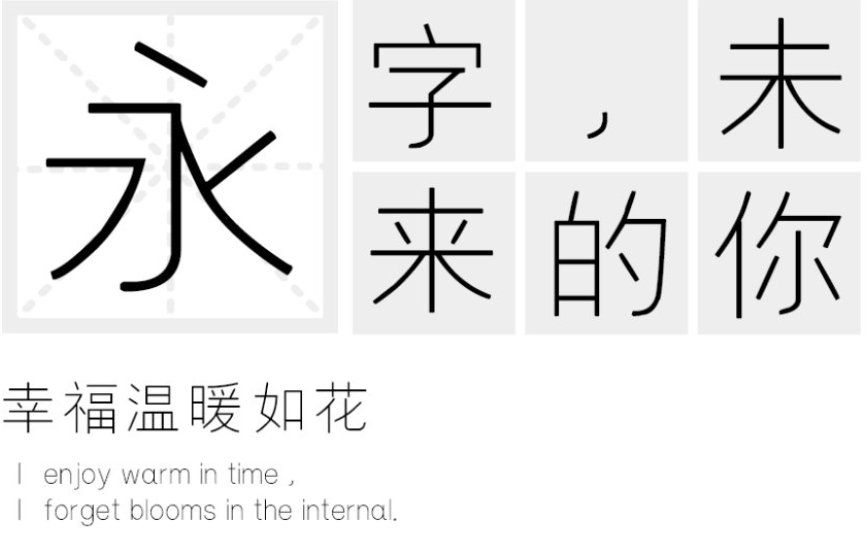
汉标细黑体发布
字体名称:汉标细黑体
字体类别: 黑体
适用场景:广告、包装、品牌形象
汉标细黑体简介:汉标细黑体字体是一款适合广告海报艺术设计的字体;细黑字形正方,笔形简练,风格简静优雅;追求远距离读取功能,笔画清晰、易于识别。可标题和正文排版,尤其适合应用在空间导视、品牌形象、包装、广告等领域。